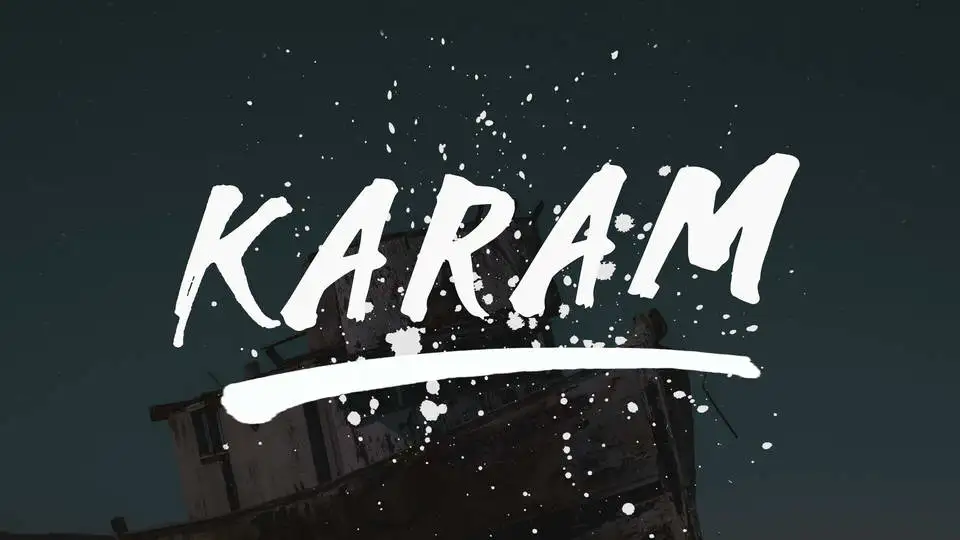
Karam Brush Font – Download Grátis
Introduzimos Karam! É uma fonte Brush perfeita. Desenhada e compartilhada por Farularjianto, a Karam é uma fonte script com textura e toque encantador. Ela se destaca como a escolha ideal para design de marca, cartas de eventos e postagens em redes sociais delicadas. Perfeito para criar um tom charmoso no seu projeto. Além disso, não hesite em contatar-nos caso você encontre alguma dificuldade ou tenha alguma pergunta. Lembramos que sempre estamos aqui para ajudar.